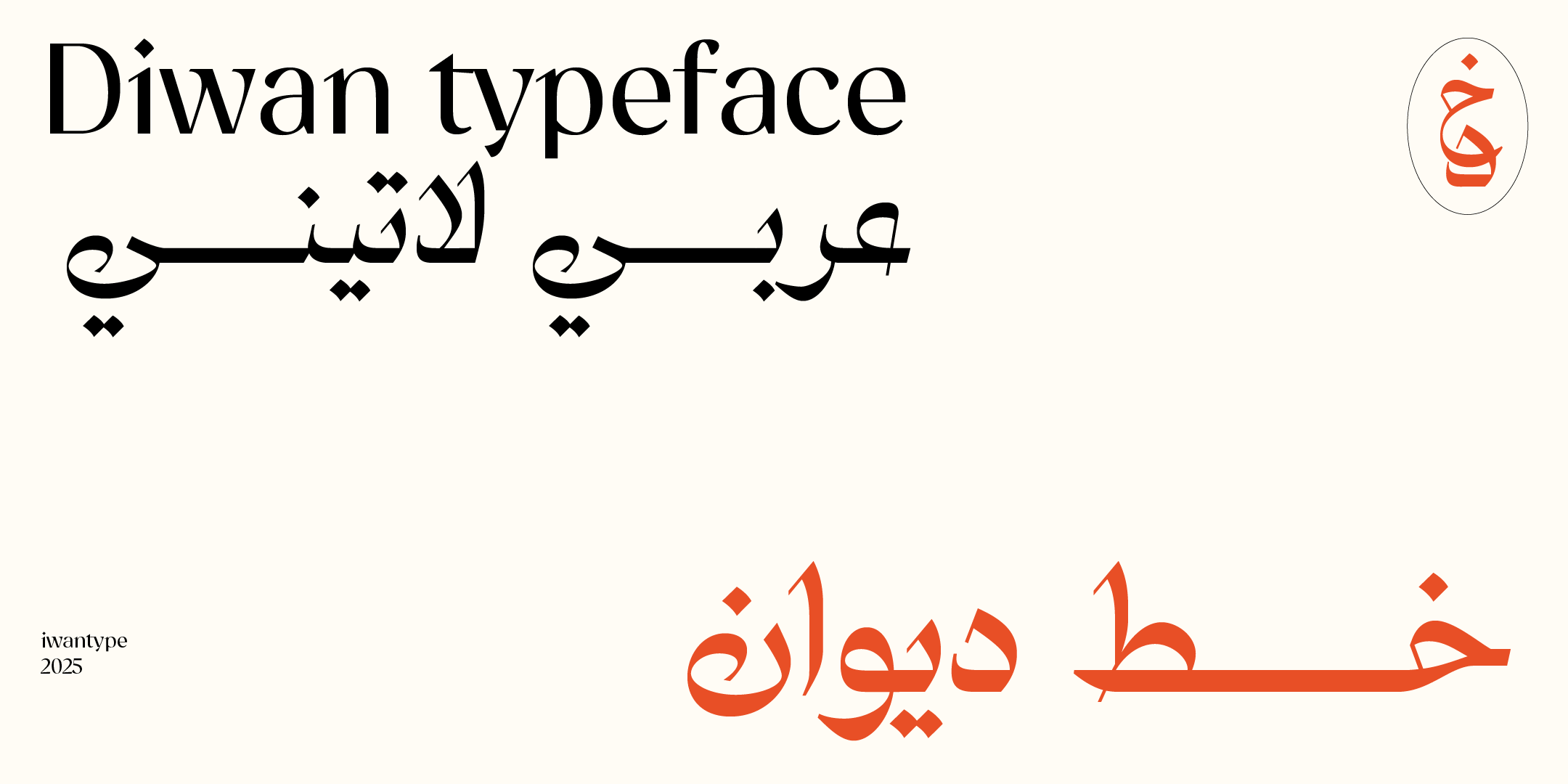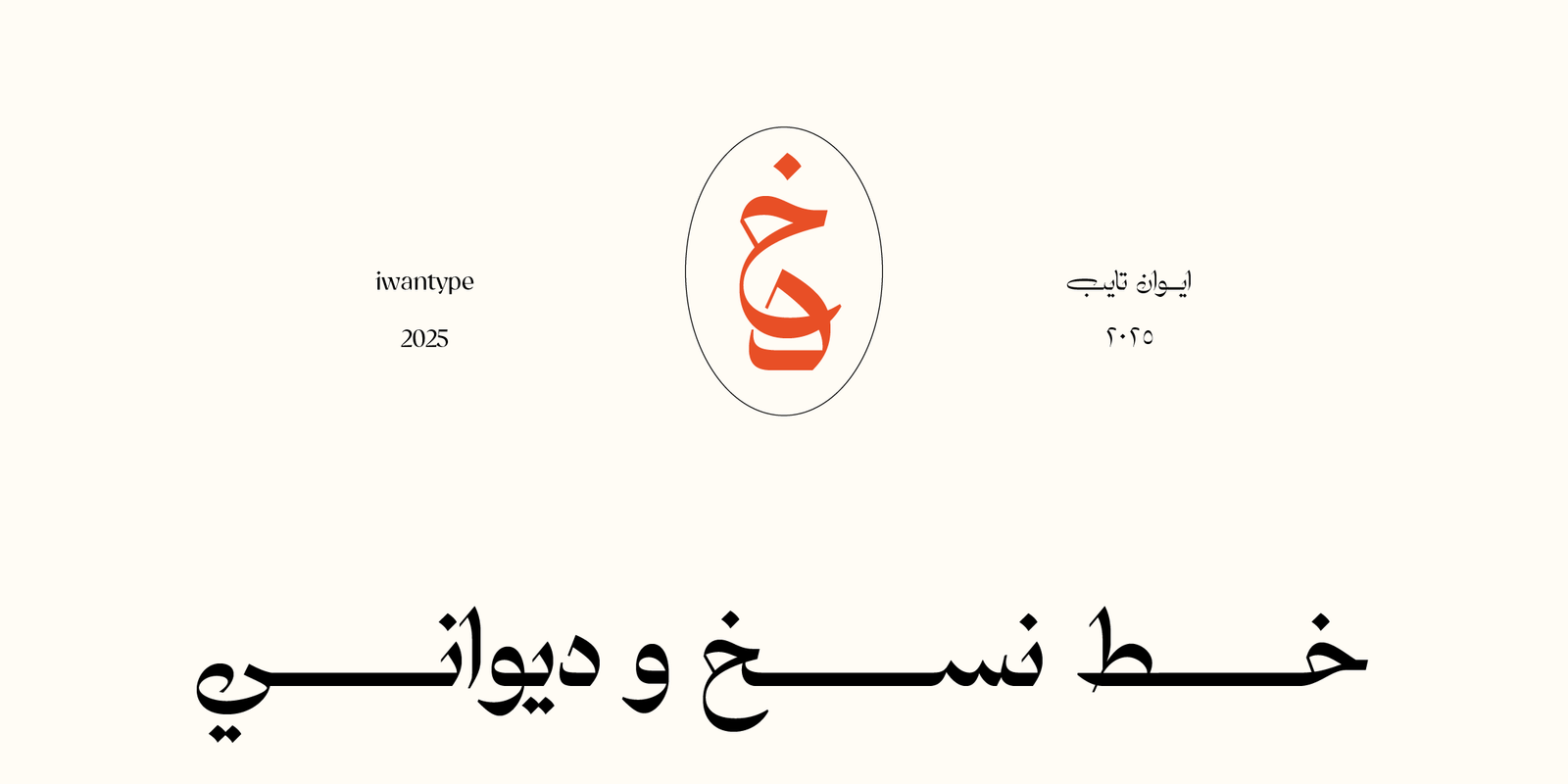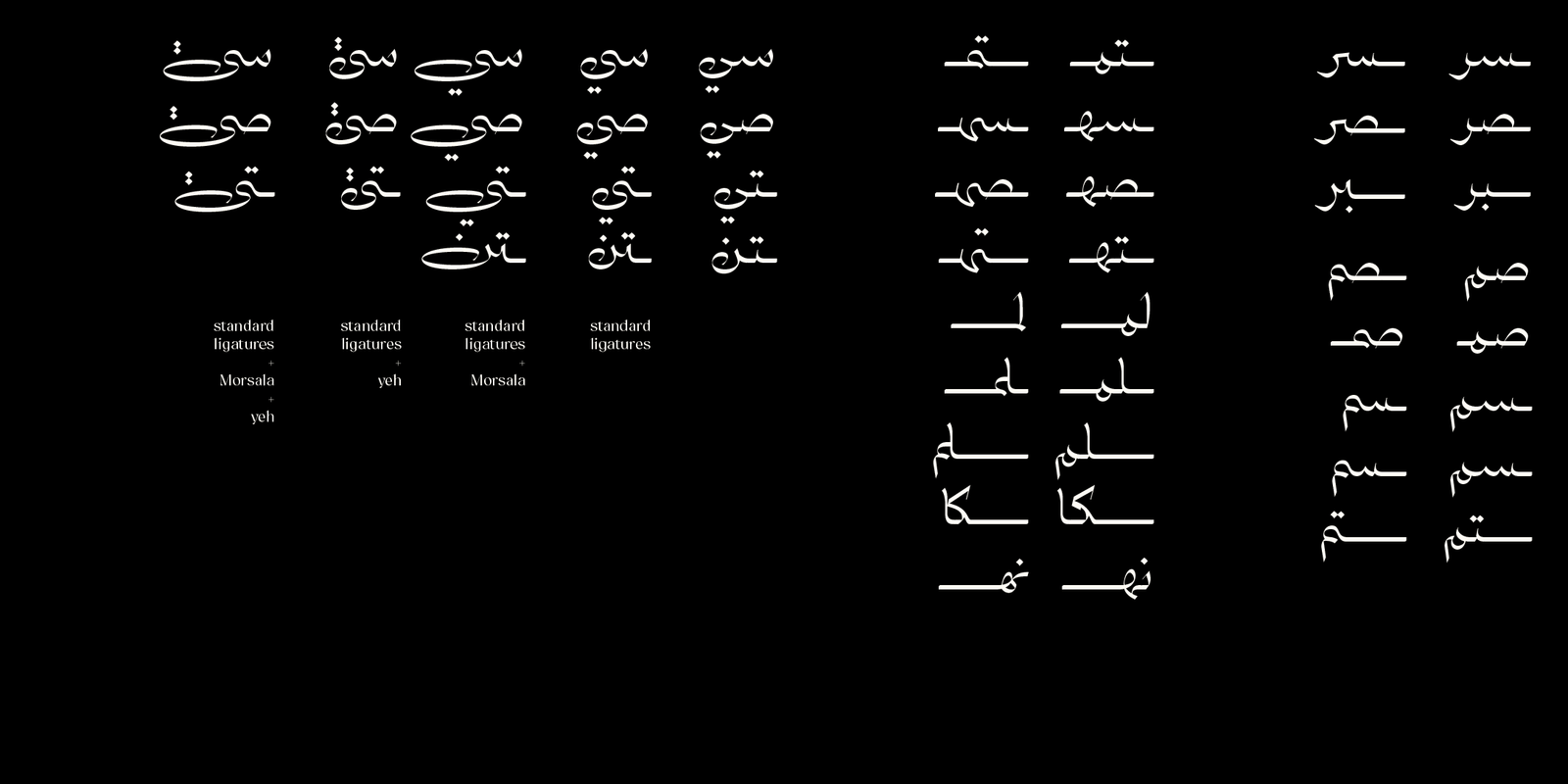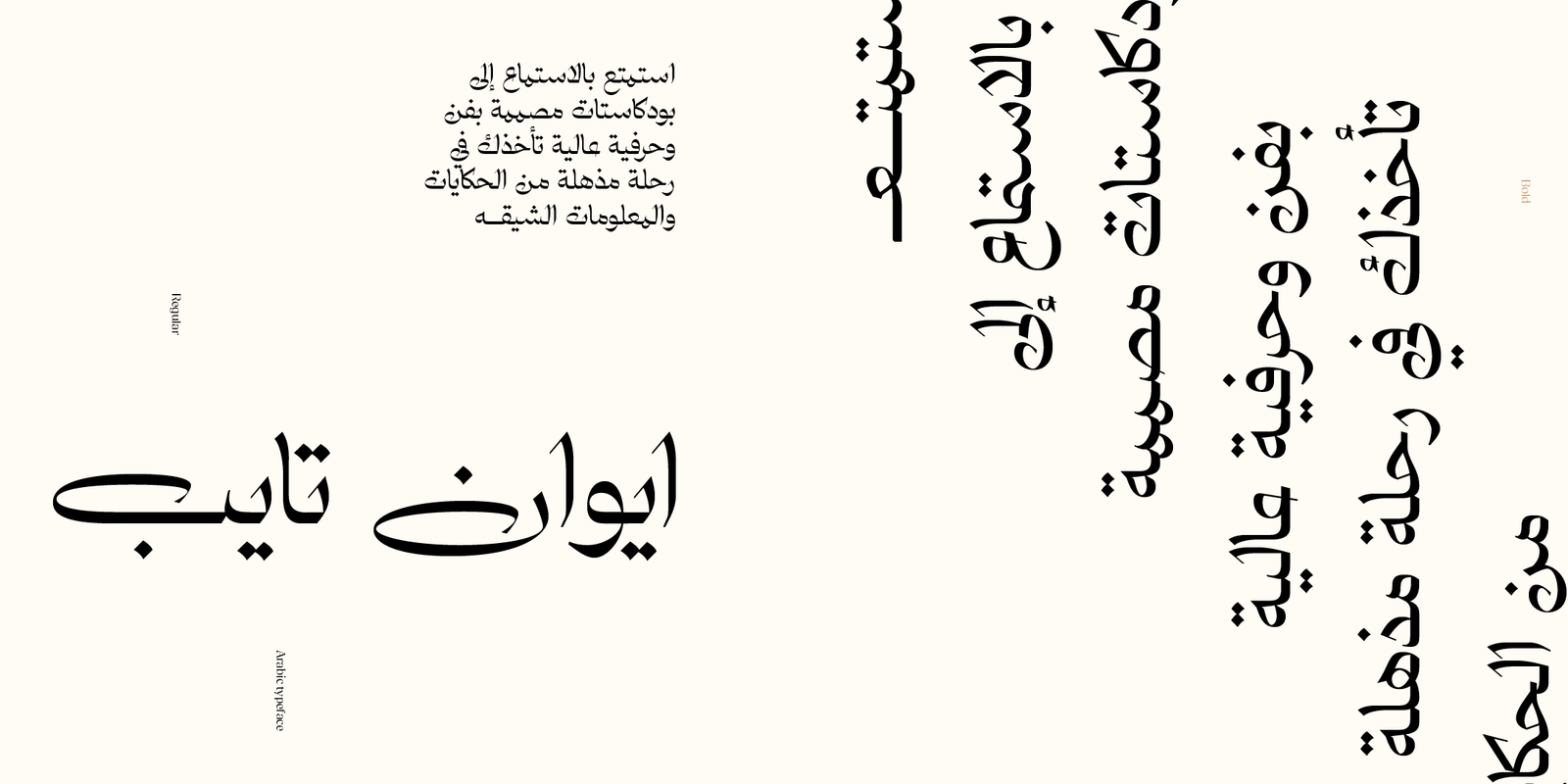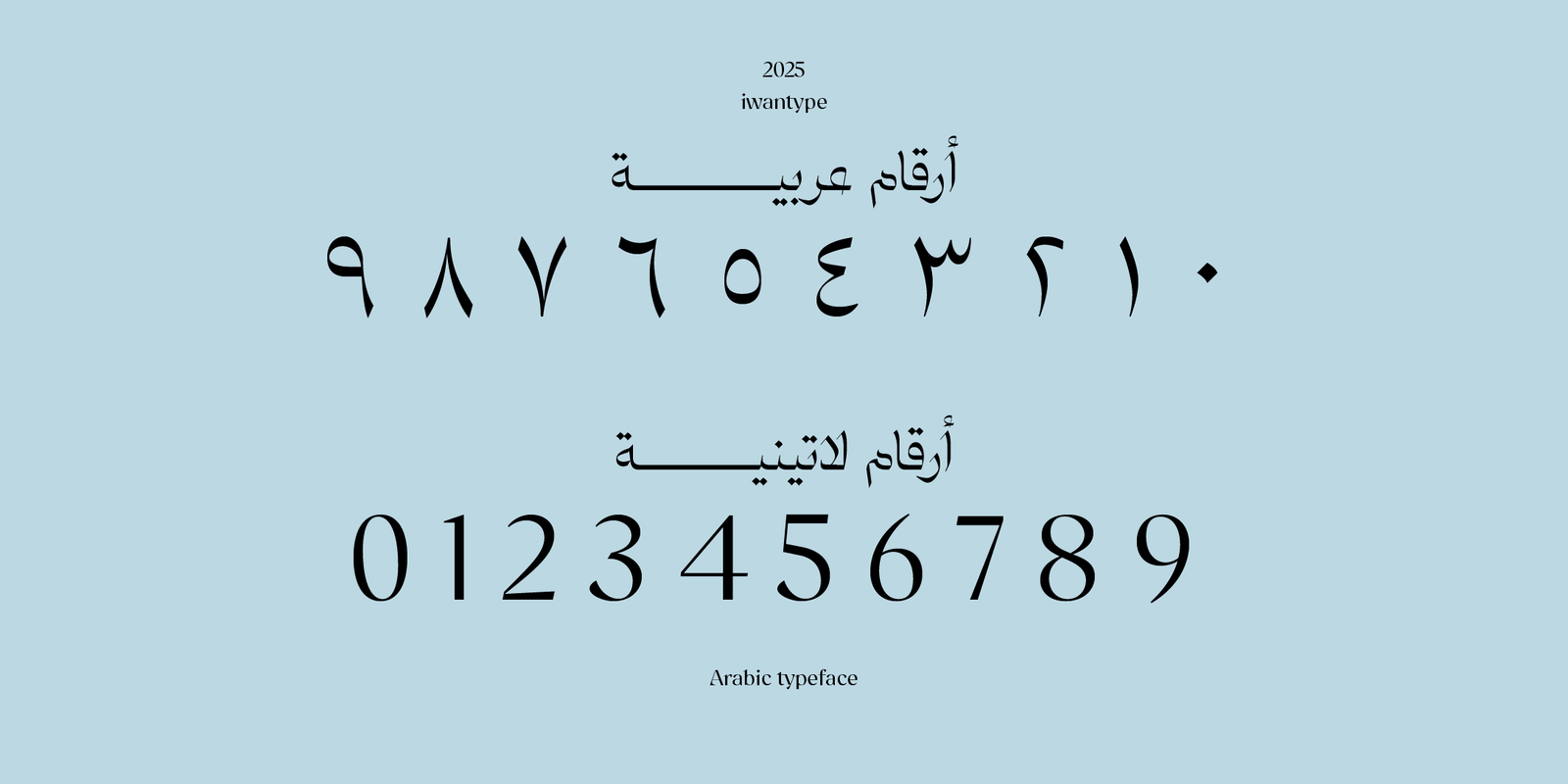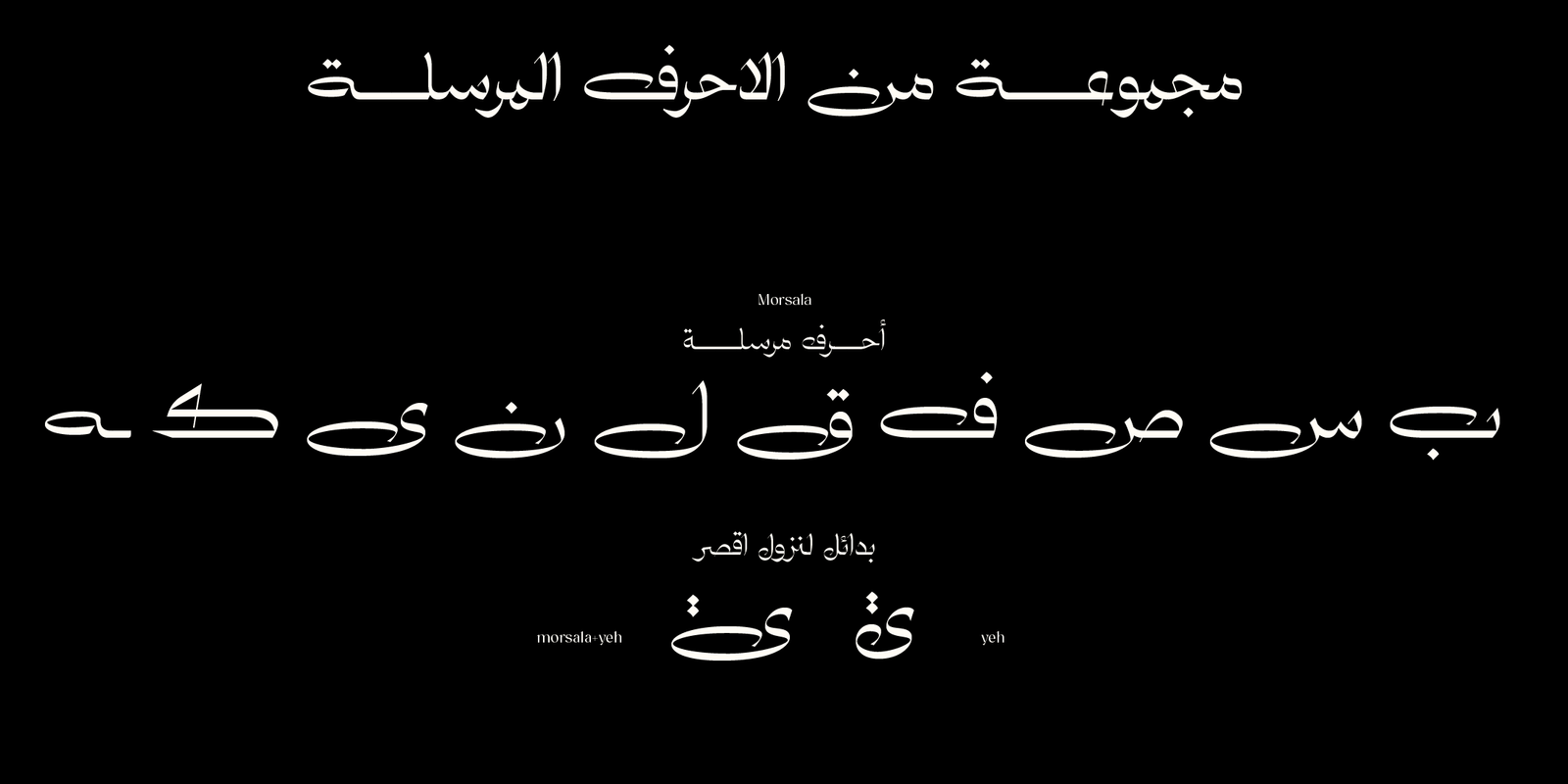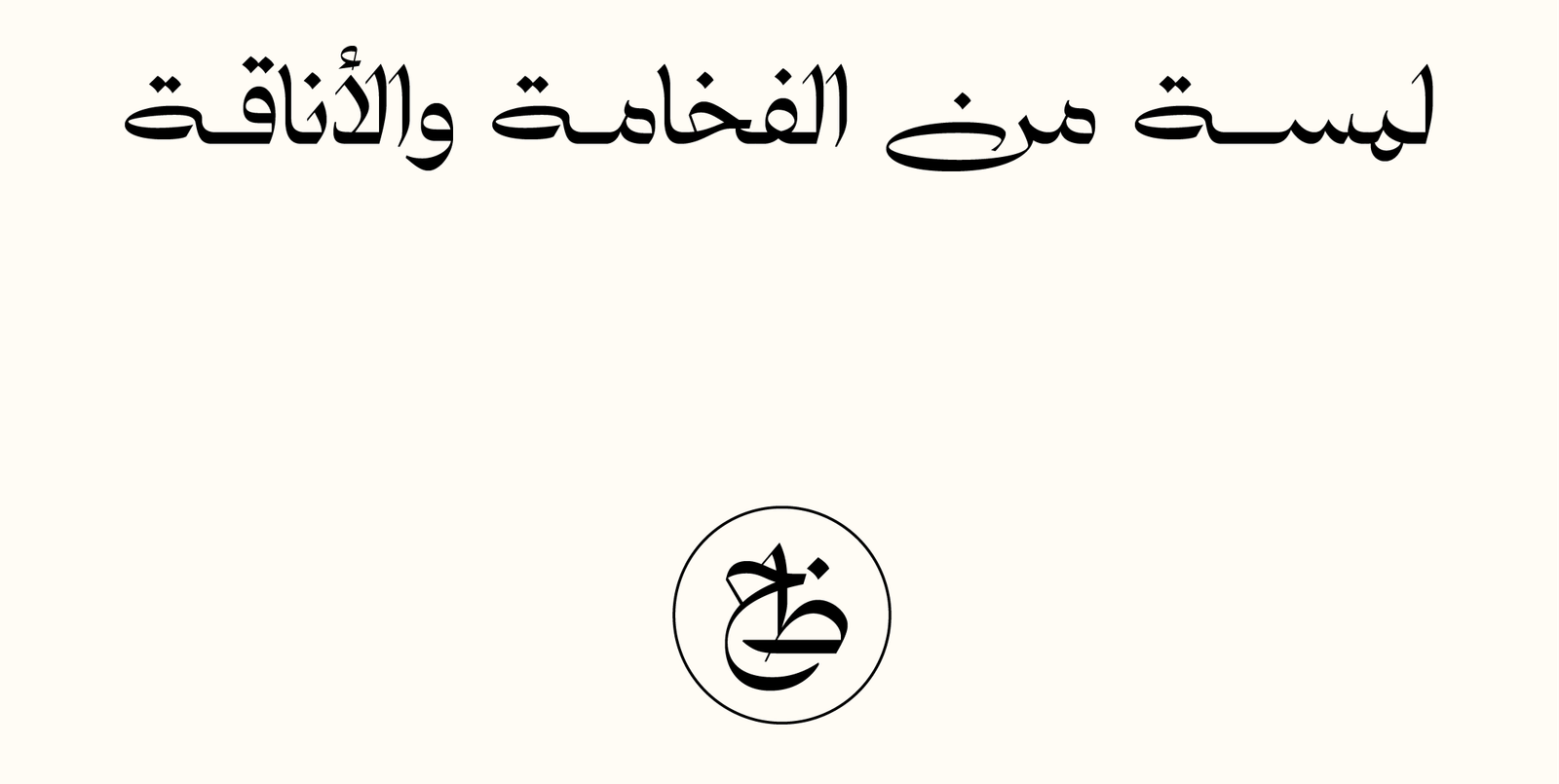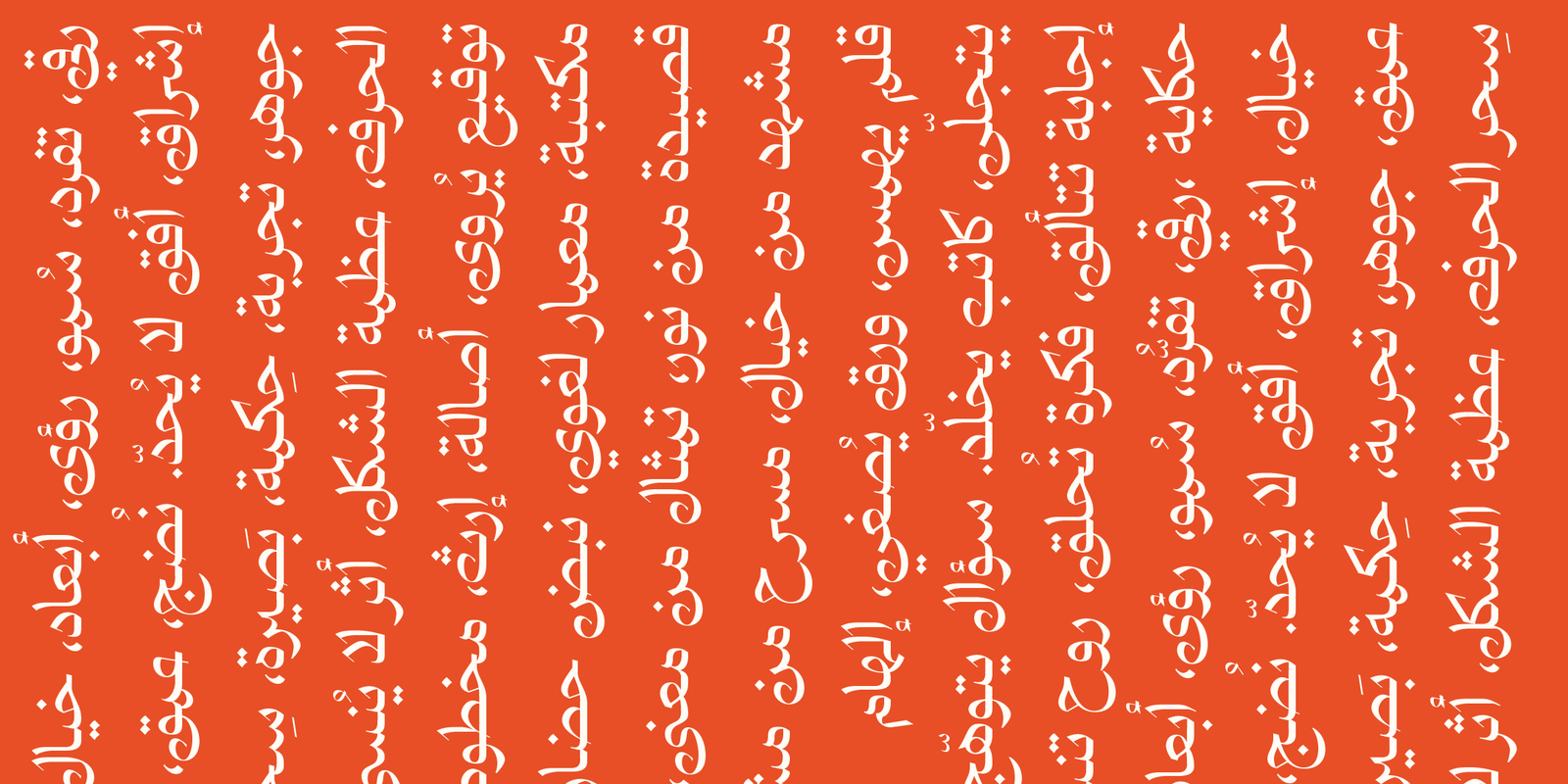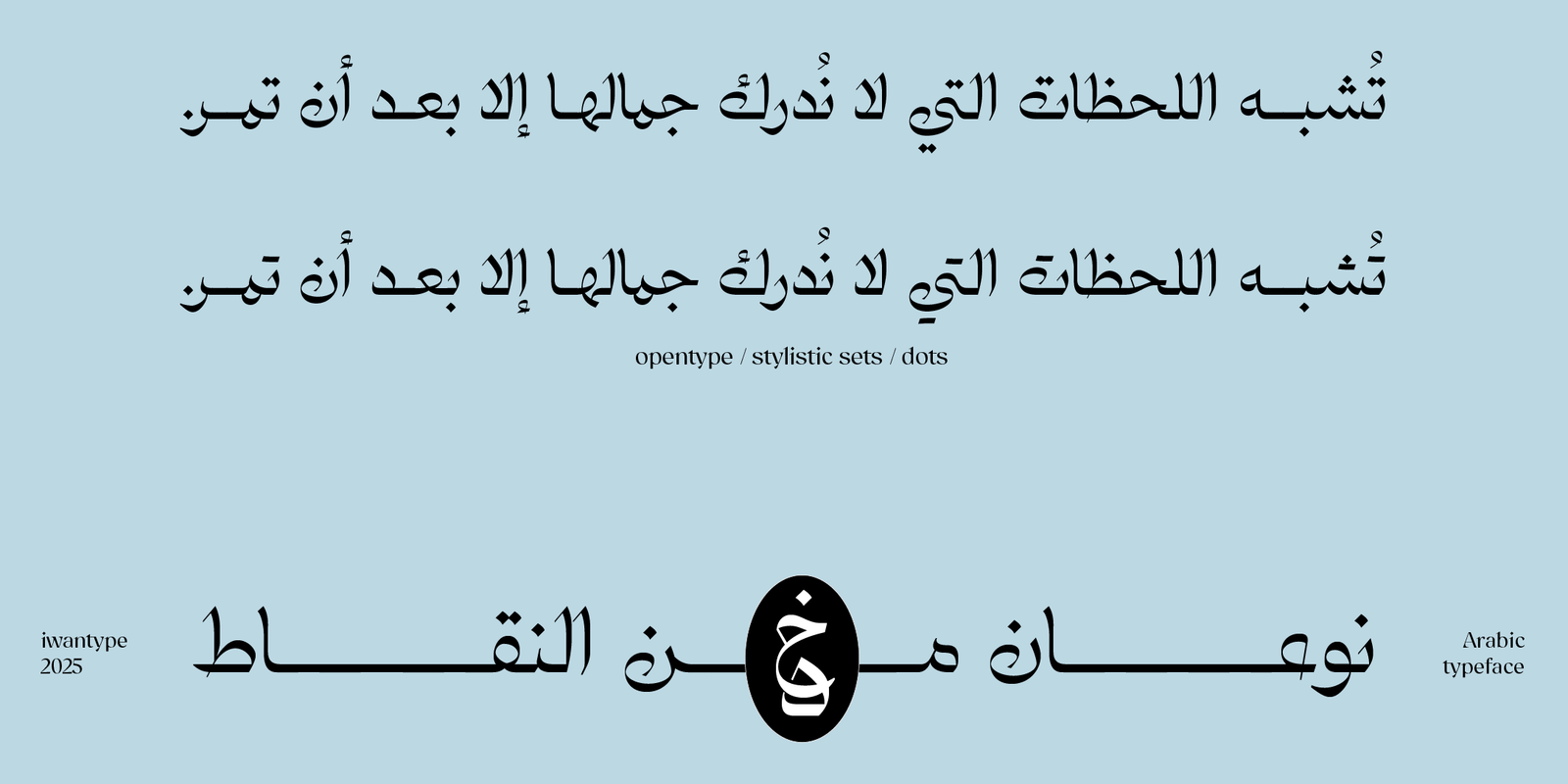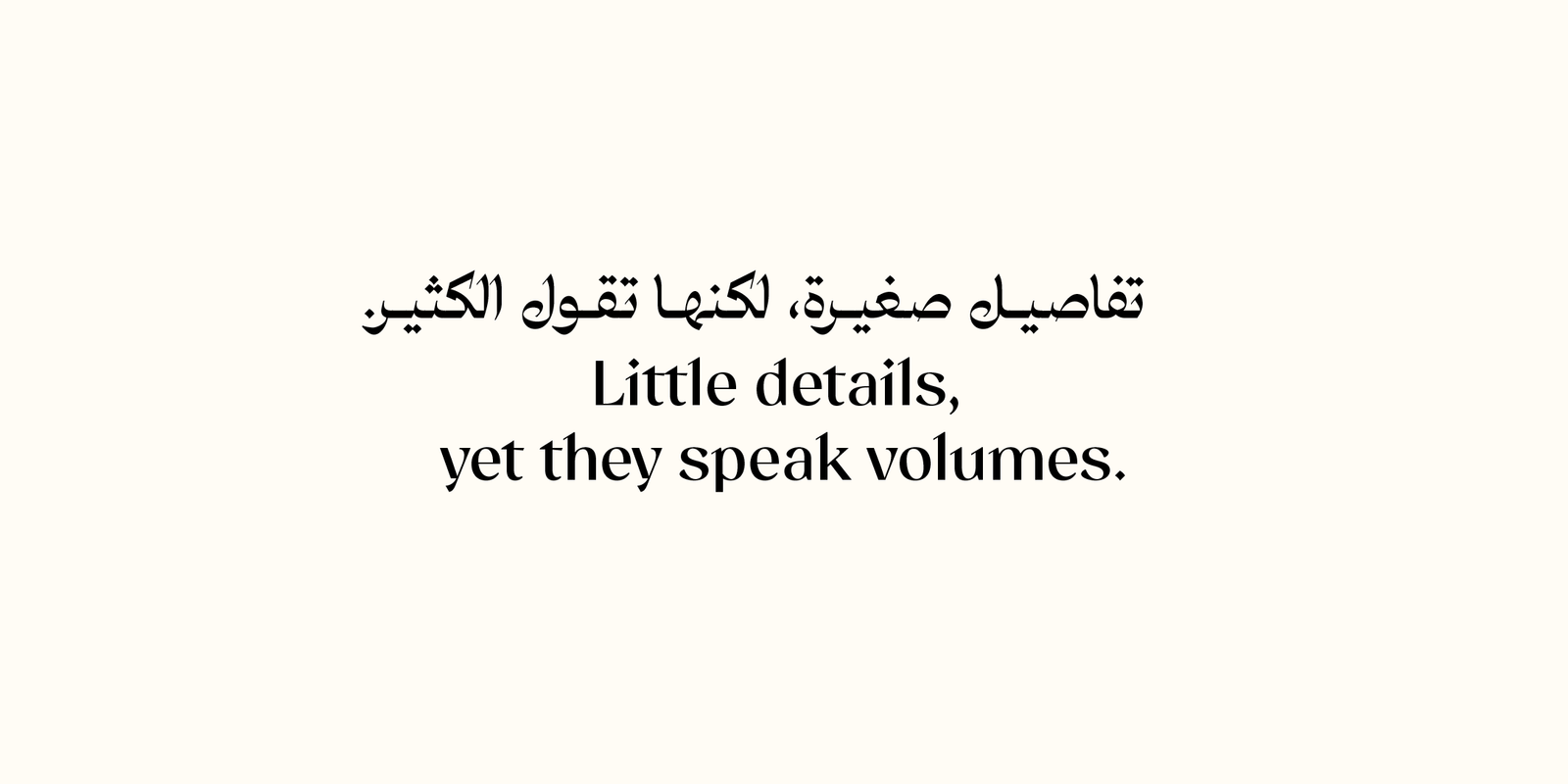
خط ديوان – نسخ – Diwan typeface
خط ديوان – خط طباعي عربي معاصر مستوحى من النسخ والديواني والرقعة
خط ديوان هو خط طباعي عربي لاتيني حديث، يتميز بتصميم فريد يمزج ببراعة بين أسلوب النسخ التقليدي ولمسات أنيقة مستوحاة من الخط الديواني وخط الرقعة.
يأتي خط ديوان في خمسة أوزان متنوعة تناسب مختلف الاستخدامات مثل العناوين الجذابة والنصوص المتناغمة، مما يجعله اختيارًا مثاليًا للتصميمات الثقافية والفنية والهويات البصرية الراقية.
يعكس خط ديوان جمالية الخط العربي من خلال الانسيابية في المنحنيات والتناسق بين تفاصيل الحروف، مع إضافة لمسة عصرية تمنحه مرونة عالية في الاستخدام.
مميزات خط ديوان:
يتضمن الخط العديد من مزايا OpenType التي تضفي عليه مرونة وتنوعًا في الاستخدام، مثل:
- الحروف المرسلة: لمسة تقليدية مستوحاة من الرقعة تضفي على النصوص جمالية خاصة.
- حرف ياء بنزول أقل: يقلل من نزول السطر، مما يعزز من انتظام النصوص.
- النقطات البديلة: توفر تنوعًا وجاذبية بصرية إضافية للنصوص.
- الحروف المركبة: تسهم في تحسين المظهر العام للنص وتزيد من سلاسته.
- توافر الأوزان: يأتي خط ديوان الطباعي بخمسة أوزان مختلفة.